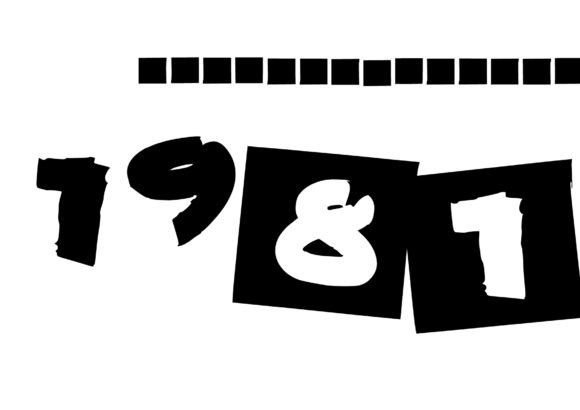
Temur Amorak Urban Bold Brush Font
Om du letar efter högkvalitativa tillgångar som Temur Amorak Urban Bold Brush Font, är detta premiumpaket ett fantastiskt val för dina kreativa projekt.
Oavsett om du skapar POD-produkter (Print on Demand), bröllopsinbjudningar eller grafik för sociala medier, är Temur Amorak Urban Bold Brush Font ett perfekt val.